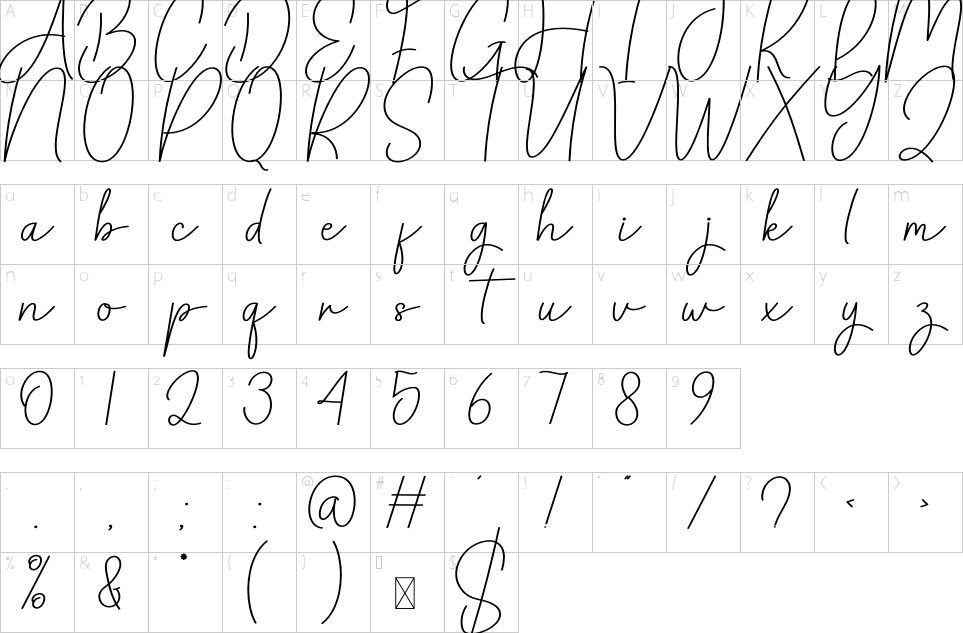
Aqui está uma descrição em português do Brasil para a página de download da font ‘Daniel Signature Font’, seguindo as instruções: Sinta-se convidado a adicionar um toque autêntico e elegante ao seu projeto digital com nossa fonte gratuita ‘Daniel Signature’. Desenvolvida pelo designer scratchones, esta fonte foi projetada para oferecer uma estética que ressoa naturalmente nas páginas de livros, no design gráfico e em materiais digitais. Com sua tipografia fluida e elegante, a ‘Daniel Signature’ é perfeita para criar um visual único e sofisticado. Quando você baixar o Daniel Signature font, será capaz de experimentá-lo em Windows e Mac, otimizando suas possibilidades criativas e tornando cada projeto mais personalizado. Com seu design cuidadosamente elaborado por scratchones, a ‘Daniel Signature’ se destaca entre outras fontes. O fato de que ela tenha sido baixada 469 vezes é uma indicação clara de sua qualidade e desempenho. Descubra o poder desta fonte única e invista no seu trabalho com um design gráfico único e sofisticado, ideal para qualquer projeto que valorize a elegância e a autenticidade.